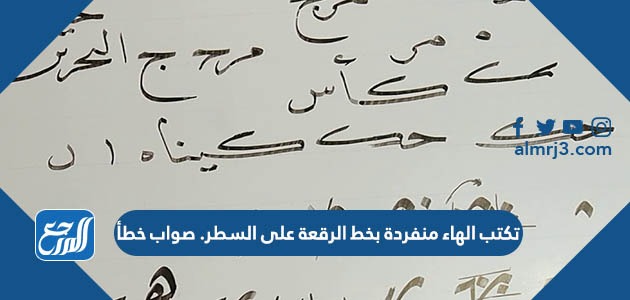
تكتب الهاء منفردة بخط الرقعة على السطر. صواب خطأ فالخط هو أحد علوم اللغة العربية التي يدرسها الطالب ضمن الفصول الدراسية، وخط الرقعة وخط النسخ أشهر نوعين من أنواع الخطوط العربية، والخط الذي يدرس الطالب قواعد حروفه وكيفية كتابتها بحالاتها الأربع في وسط وأول وآخر الكلمة سواء أكانت متصلة أو منفصلة هو خط الرقعة، من هذا المنطلق سوف نسلط لكم الضوء من خلال سطورنا التالية في موقع المرجع صحة هذه العبارة من خطأها، ونرفق لكم في نهاية هذا المقال قواعد خط الرقعة.
الهاء هو الحرف السادس والعشرين من الأبجدية الألفبائية العربية، وهو أحد الحروف الهامسة وهو حرف رخو يخرج من أقصى الحلق، وفي علم النحو حرف الهاء يمثل هاء الغائب وها الغائبة، الضميران اللذان يعربا في محل نصب مفعول به عندما يتصلا بفعل وجر بالإضافة إذا اتصلا باسم، وهاء الغائب أيضًا تستخدم نحوياً لمعرفة تعدي الفعل من لزومه، وعند كتابة حرف الهاء بخط الرقعة يتم كتابته بشكل منفرد وملامساً للسطر، ومن هذا نستنتج أن الجواب الصحيح لهذا السؤال هو:
- عبارة صحيحة.
وكل حرف من حروف اللغة العربية الثماني والعشرين له قواعد كتابة بخط الرقعة خاصة به، وسوف نتعرف على هذه القواعد معاً.
قواعد خط الرقعة
كل حرف من حروف الأبجدية الألفبائية الثماني والعشرين له قاعدة، مع ذلك يمكن تلخيص قواعد خط الرقعة بما يلي:
- تكتب أغلب حروف اللغة العربية فوق السطر مثل الراء والزاي والياء وغيرها، والبعض منها يكتب على السطر مثل الهاء والباء والتاء والثاء.
- بعض أحرف الأبجدية تكتب نصفها فوق السطر والنصف الآخر تحته مثل حروف العين والغين والجيم والحاء والخاء والميم بآخر الكلمة متصلة ومنفصلة.
- حرف الهاء يكتب على السطر في أول الكلمة وفي آخرها وفي الشكل الكامل، بينما يكتب على السطر وينزل تحته بشكل مائل في وسط الجملة.
- حرفي السين والشين يكتبان بلا أسنان في خط الرقعة.